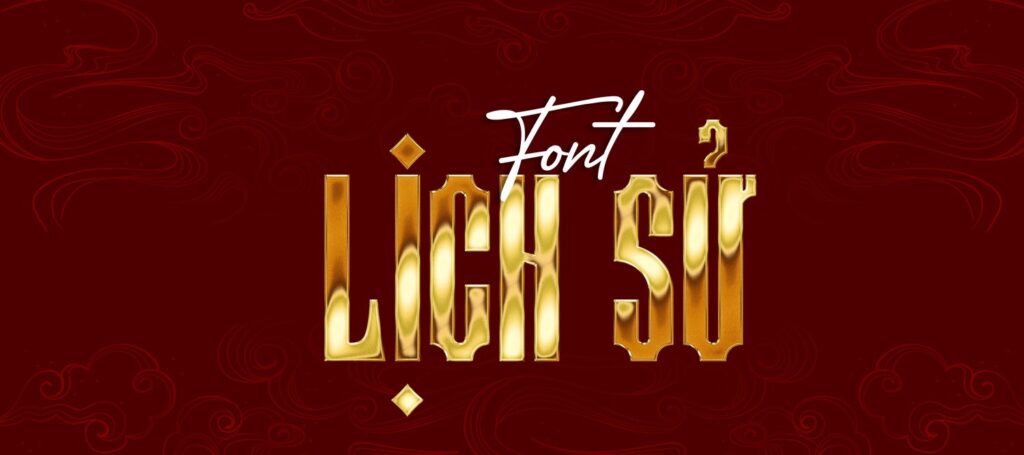
Trong thiết kế kiến trúc và đồ họa, những bộ font chữ mang phong cách hoài cổ, phục dựng từ các tư liệu xưa cũ luôn có sức hút riêng biệt. Việc sử dụng font chữ lịch sử Việt hóa giúp tái hiện lại không gian văn hóa truyền thống, tạo nên sự trang trọng và chiều sâu cho tác phẩm.
Đặc điểm thẩm mỹ của font lịch sử Việt hóa
Dòng font này thường lấy cảm hứng từ các bản khắc gỗ, thư tịch cổ hoặc các kiểu chữ phổ biến trong những thập niên trước. Điểm nổi bật của font lịch sử Việt hóa là các nét chữ thường có độ dày ổn định, cấu trúc mang tính đối xứng cao hoặc mô phỏng nét cọ viết tay truyền thống. Phiên bản Việt hóa giúp giải quyết vấn đề lỗi hiển thị các ký tự đặc biệt, đảm bảo các dấu thanh phối hợp nhịp nhàng với thân chữ mà không làm mất đi tinh thần xưa cũ của bộ gốc.
Sự tinh tế của các bộ font này còn nằm ở khả năng tạo ra sự kết nối giữa quá khứ và hiện tại. Những đường nét không quá cầu kỳ nhưng chứa đựng sự chân thực, giúp bản thiết kế mang vẻ đẹp bền bỉ và trang trọng. Đây là phương án phù hợp cho các dự án yêu cầu tính tự sự cao, muốn truyền tải thông điệp về lòng tự hào dân tộc và sự trân trọng đối với các giá trị di sản.
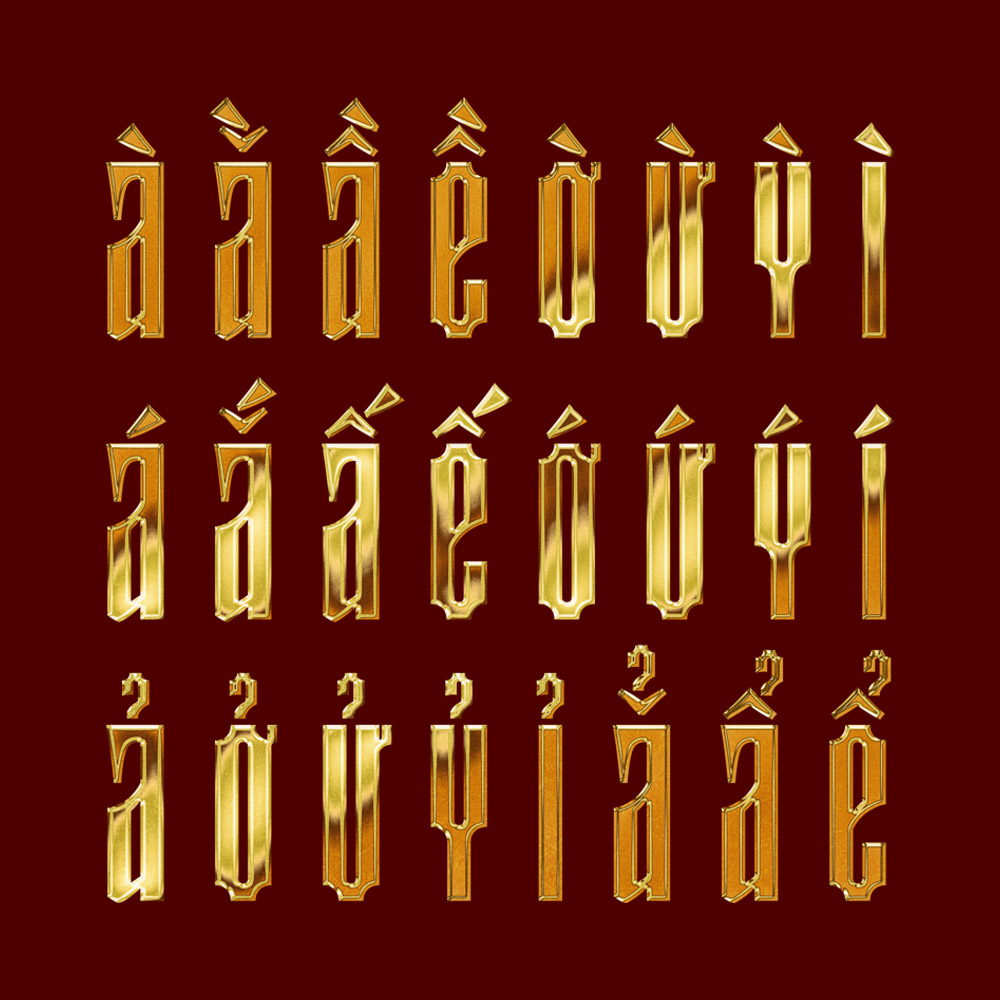
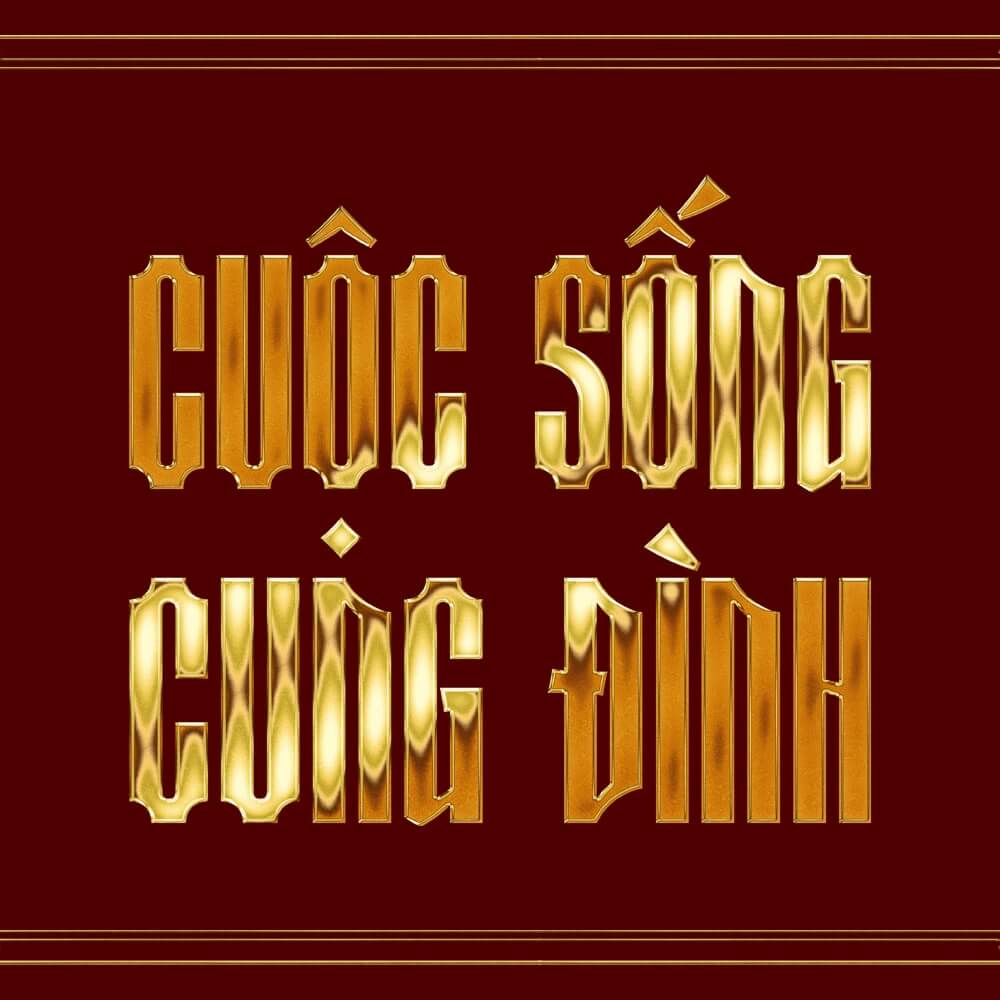
Thông tin kỹ thuật và link tải font chữ lịch sử Việt hóa
Gợi ý phối hợp: Font phong cách lịch sử thường có cá tính rất mạnh. Bạn nên phối hợp chúng cùng một font chữ không chân (Sans-serif) hiện đại cho phần nội dung chi tiết để tạo sự cân bằng, giúp bản thiết kế vừa mang hơi thở hoài cổ vừa đáp ứng được tiêu chuẩn đọc hiểu rõ ràng.
03 Ứng dụng của font việt hóa lịch sử trong kiến trúc và đời sống
Nhờ vẻ ngoài mang tính biểu tượng và sự trang trọng, bộ font này mang lại giá trị thực tế cao khi được đưa vào các hạng mục quảng bá và trang trí công trình:
- Bảng nhận diện cho Homestay phong cách cổ: Những nét chữ hoài cổ rất ăn ý khi xuất hiện trên chất liệu gỗ, đồng hoặc gạch gốm tại các khu nhà lắp ghép nghỉ dưỡng. Điều này giúp du khách cảm nhận được không gian xưa cũ ngay từ khi bước chân vào công trình.
- Thiết kế hồ sơ phục dựng di tích: Sử dụng font chữ lịch sử Việt hóa để trình bày tiêu đề các bản vẽ kiến trúc, thuyết minh dự án bảo tồn giúp hồ sơ trở nên chỉn chu và phù hợp với bối cảnh lịch sử của dự án.
- Trang trí không gian nội thất văn hóa: Bạn có thể dùng font này để cắt chữ nổi laser làm điểm nhấn tại phòng khách, khu vực trưng bày hoặc các quán cafe mang phong cách cổ điển, tạo nên dấu ấn độc đáo cho không gian sống.
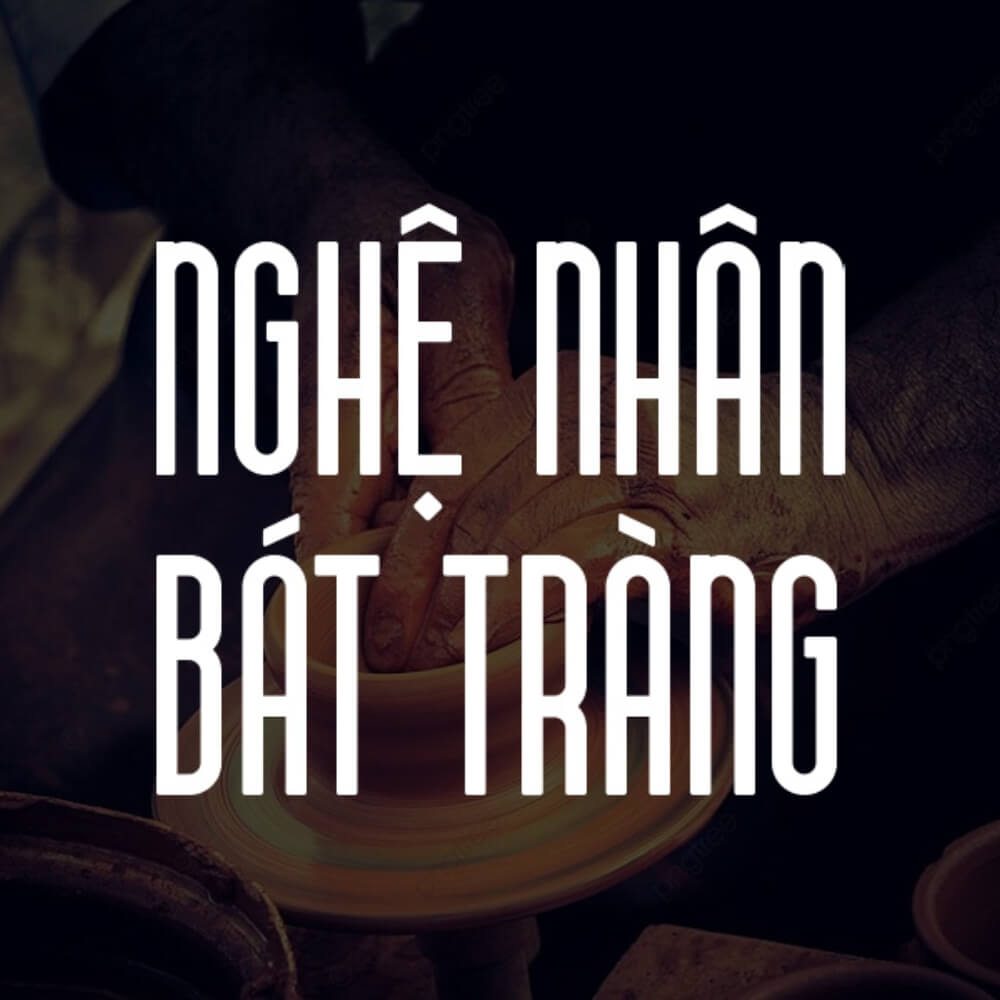
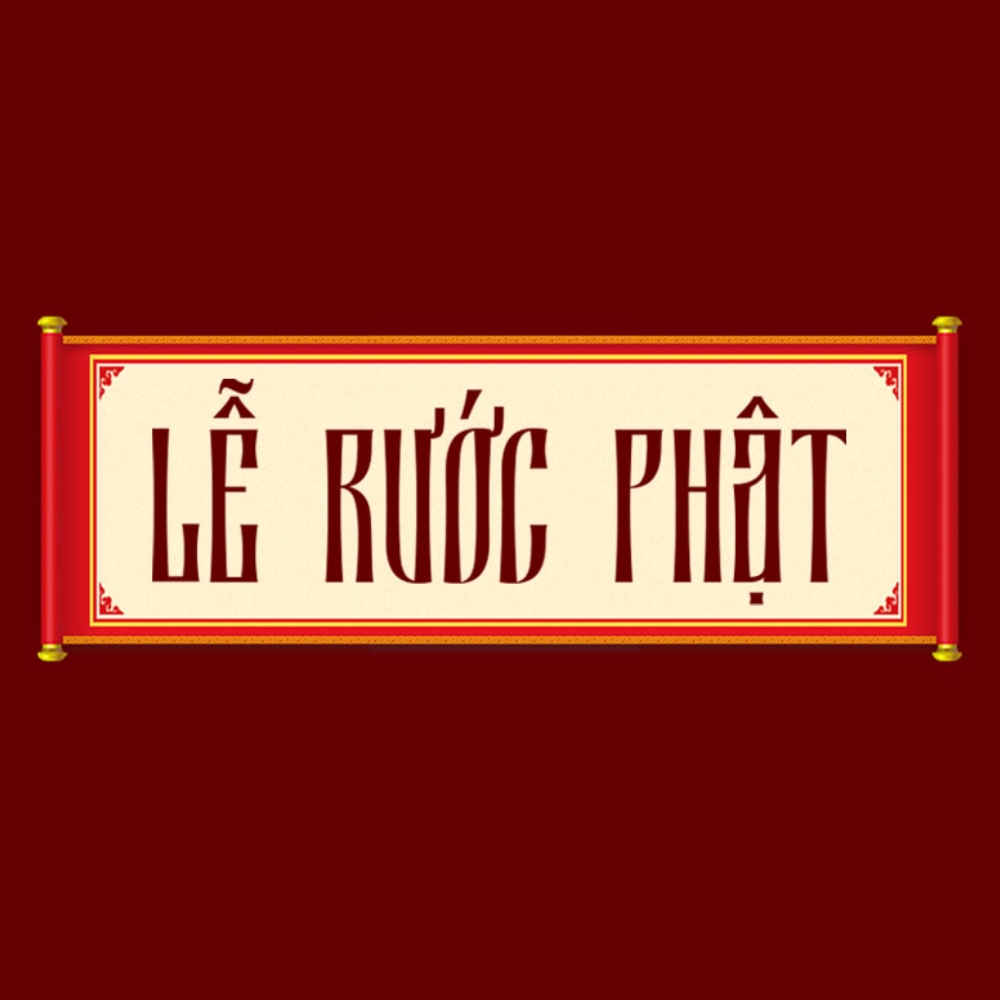
03 Lưu ý để sử dụng font lịch sử Việt hóa chuyên nghiệp
Để khai thác hiệu quả vẻ đẹp của dòng font đặc thù này mà không làm rối mắt người xem, người thiết kế nên lưu tâm một số kinh nghiệm sau:
- Lựa chọn màu sắc phù hợp: Các font mang tinh thần lịch sử phát huy hiệu quả thị giác cao khi phối cùng các tông màu trầm như đỏ bordeaux, vàng đồng, đen mực tàu hoặc nâu đất. Tránh các màu sắc quá chói lọi làm mất đi vẻ trang nghiêm của bộ chữ.
- Kiểm soát mật độ chữ: Chỉ nên sử dụng font lịch sử cho các tiêu đề chính hoặc các đoạn văn ngắn. Việc lạm dụng cho các đoạn văn bản dài sẽ gây khó đọc và làm mất đi trọng tâm thẩm mỹ của bản thiết kế.
- Chú ý đến khoảng cách dòng: Một số bộ font lịch sử có chân chữ dày hoặc nét uốn lượn rộng, bạn nên để khoảng cách dòng thoáng một chút để các ký tự không bị chồng lấn, giữ được sự minh bạch cho thông tin.